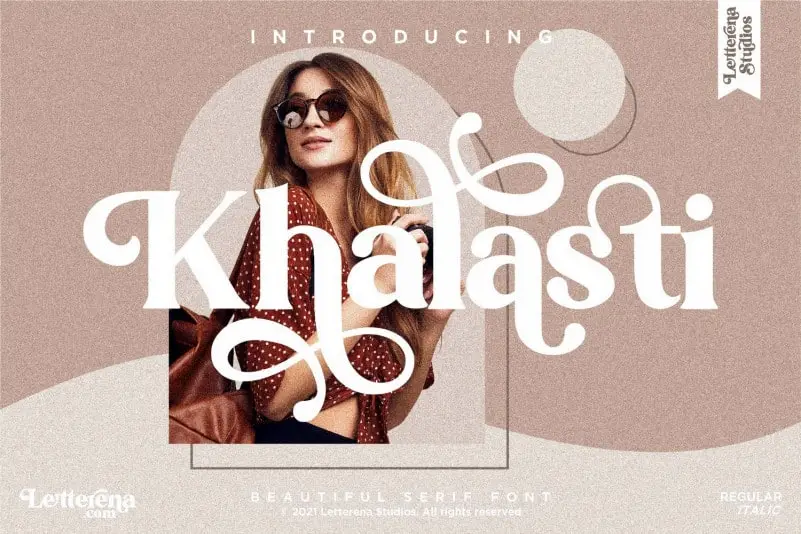
Khalasti Serif Font – Download Grátis
Khalasti Serif é uma fonte serif que foi criada por Letterena Studios com swashes. Esta fonte não apenas se destaca pelo seu estilo único e sofisticado, mas também oferece alternativas estilísticas e ligaturas para torná-la ainda mais singular. Suas características distintivas a tornam perfeita para uma ampla gama de projetos como logos, embalagens de produtos, materiais de marca, ilustrações, capas de livros, cartões de nome, convites, encomendas, etiquetas, fotografias, marcas e até eventos especiais. Khalasti Serif é um excelente complemento para qualquer projeto que busque trazer elegância e sofisticação à sua obra com uma fonte serif excepcionalmente refinada. Além disso, a fonte está disponível no site da 99designs, oferecendo designers e criadores de produtos uma opção fácil e confiável para incluir uma fonte serif elegante em seus projetos. Com Khalasti Serif, você pode agregar um toque sofisticado e único a qualquer projeto que exija um toque especial de beleza e qualidade.